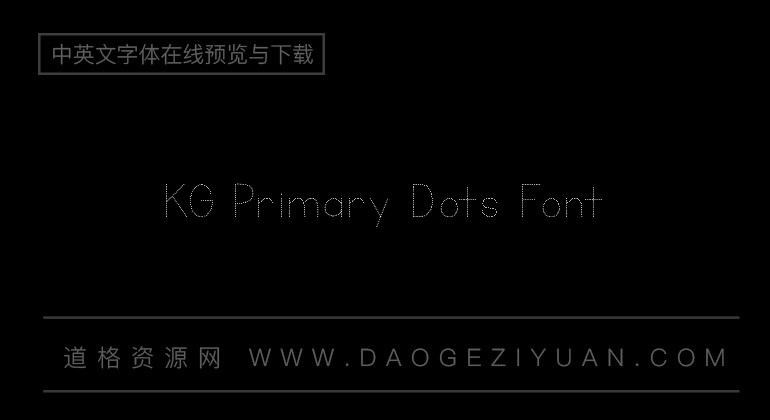
KG Primary Dots Font
KG Primary Dots是一种带有圆点的手写风格字体,主要用于教育和儿童相关的设计项目。这种字体的特点是字母和数字的外形是由圆点和线条组成的,看起来非常可爱和活泼。它可以用于幼儿园、小学或其他儿童教育相关设计项目,例如教材、海报、卡片等。由于其简单而易于阅读的特点,KG Primary Dots字体也适用于一些书信或笔记应用程序,比如记录日记或写便笺。
KG Primary Dots Font是一款非常不错的手写艺术字体,具有很好的视觉感,适合于文化类的宣传设计、商业类品牌的广告和产品包装设计以及个性化文字排版等较多场景。